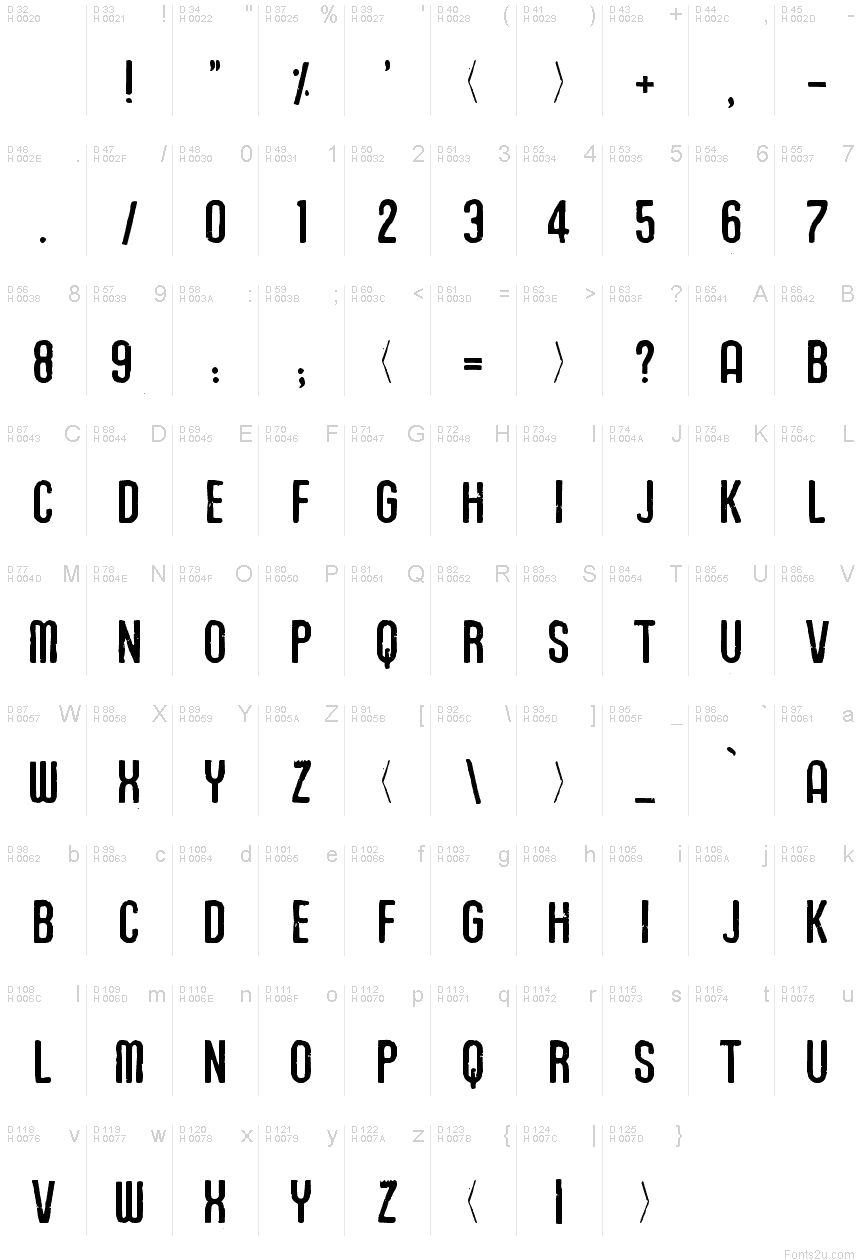
Union Agrochem Charkrapetch
Union Agrochem Charkrapetch od Polenimschaufenster prod. to darmowy krój displayowy o erodowanym charakterze. Wysokie, tępo zakończone wielkie litery oraz nierówne, przetarte krawędzie przywołują na myśl napisy na starych fabrykach. Litery są wąskie i solidne, ale dzięki wyszczerbieniom i zadrapaniom nie sprawiają wrażenia zbyt surowych czy dopracowanych.
Krój świetnie sprawdza się na plakatach, opakowaniach, ulotkach muzycznych, w napisach tytułowych oraz w brandingu, który potrzebuje industrialnego, „zmęczonego” klimatu, bez popadania w typowy vintage script. Jako darmowy font, najlepiej wypada w krótkich liniach, na okładkach i w wyrazistych logotypach, gdzie te „blizny” na literach natychmiast przyciągają wzrok.